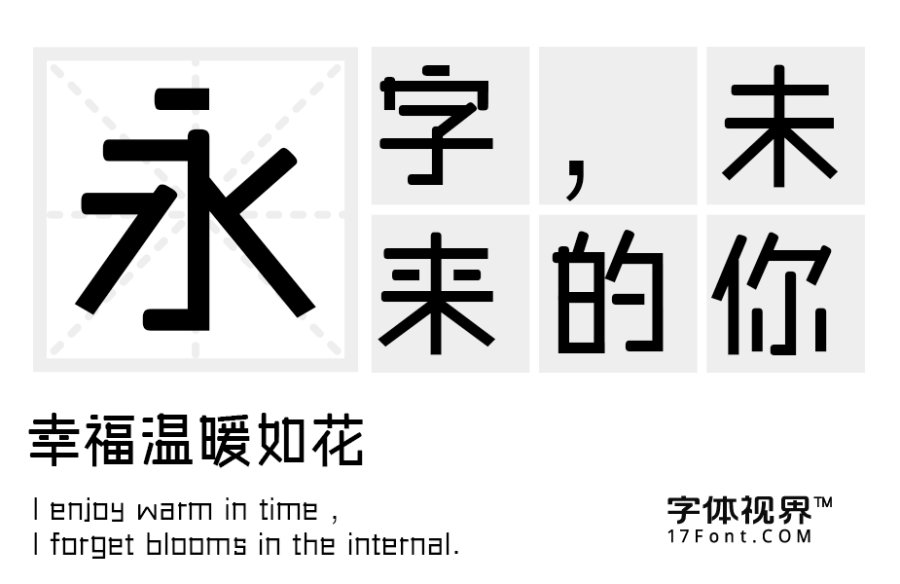
三极傻黑简体发布
字体名称:三极傻黑简体
字体类别: 创意字体
三极傻黑简体简介:三极傻黑简体是一款几何型构成的作品。整体风格率真,直接。字体稳重简洁,笔画平直、粗细匀称,起笔为圆头温柔可爱,收笔平直天真率气,又有强烈的个性。风格年轻、富有亲和力。它的灵感来源于管状物体,直接简单,坚韧不屈,给人一种直接干练的感觉。
三极傻黑简体预览图展示: